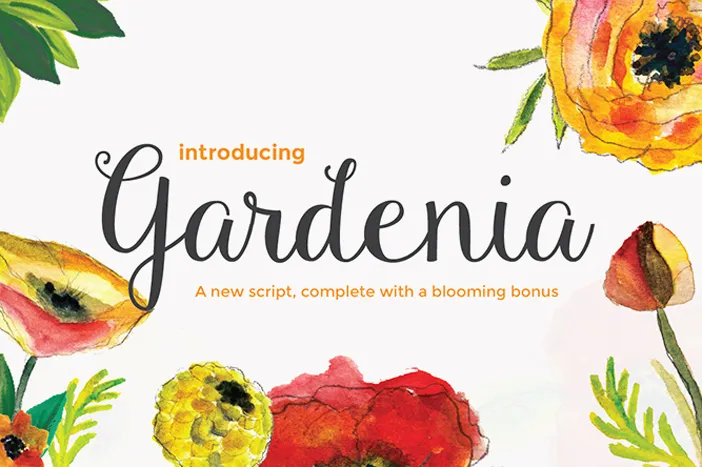
Gardenia Script Font – Fonte Grátis
Gardenia Script Font
Introduzimos a Gardenia Script Font! Esta nova tipografia foi criada pela profissional Emily Spadoni. Inspirada na primavera, a Gardenia Script traz personagens traçados à mão que adicionam um toque quente a qualquer projeto. Desenhadas de forma artesanal, estas letras são uma ótima escolha para quem procura personalidade e sofisticação em seus materiais digitais. Emily Spadoni trouxe essa fonte ao mundo da design gráfico com todo o seu conhecimento e paixão pela arte, oferecendo aos designers um recurso visual que reflete a delicadeza e harmonia das flores nas paisagens primaveris. Seja para criar cartões de aniversário únicos ou trabalhos profissionais, Gardenia Script é uma fonte perfeita para aqueles que buscam um charme especial em suas criações digitais.